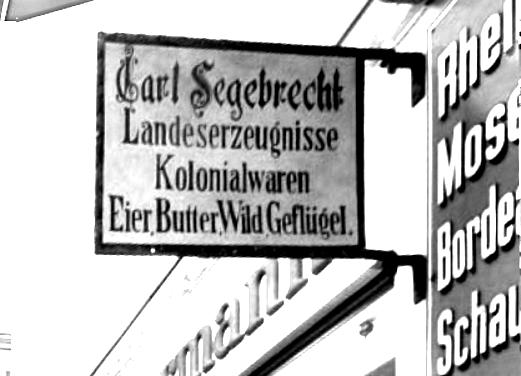
Schriften für Ladenschilder etc. um 1900-1910, was passt?
ich suche passende Schriften für Laden- und Hinweisschilder, ca. von 1900 bis 1910. Nicht unbedingt Frakturschriften. Siehe Schild im Anhang ab Zeile "Landeserzeugnisse". Ich bin Mitglied bei einer Museumseisenbahn und wir möchten den Bahnhof mit entsprechenden Schildern ausstatten. Alle Vorschläge sind willkommen, ich lege mich nicht unbedingt auf das Schriftbild im Anhang fest.
vor 4 Stunden schrieb Ralf Herrmann:
Nicht böse sein, aber das ist falsch gedacht. Die Schilder können durchaus mit bereits etablierten, und damit auch (wesentlich) älteren, Schriften versehen sein. Ich denke da gerade an die Breite Halbfette (Schelter-) Grotesk ... Kurz: Aus dem Jahr 1860, die freie Schrift Works Sans ist da ziemlich ähnlich ...
Hier zwei Postings mit Bezug:
Aber auch andere Schriften kommen da in Frage: Die alten Schriftmuster der Akzidenz Grotesk aus der Zeit von vor 1900.
Und dann sind da noch die Vorläufer der Schriften nach DIN 1451. Da hat Peter einiges im Programm ...
vor 4 Stunden schrieb catfonts:
dann schau mal bei mir, catfonts.de, da ist bestimmt im Stil passendes dabei.
Das waren nun die Serifenlosen. Das von mir geschriebene gilt auch für Antiqua.  Hier was für 1900 ...
Für die Lettern auf dem Schild ist die Vorlage eine der alten, schmal laufenden Schriften aus der Zeit um oder kurz vor 1900 gewesen.  Ich greife mir mal zwei Beispiele raus:
Das nächste Beispiel sind eigentlich drei Schriften mit Namen Theano, alle vom gleichen Designer:
Diese Schriften sind bei mir im E-Katalog auf der Festplatte übrigens in der Unterrubrik Science (Wissenschaft) abgelegt. Diese Schriften kennt man meistens nur noch aus ganz alten Lehrbüchern.
Hier findet man ganz viele thematische Listen: http://www.fontscape.com/
Categories -> Period -> ... Und dann gibt es aus dem passenden Zeitraum einiges:
Ich würde die Rubrik Jugendstil vorschlagen: http://www.fontscape.com/explore?6QH
vor 6 Stunden schrieb Uwe Borchert:
Nicht böse sein, aber das ist falsch gedacht. Die Schilder können durchaus mit bereits etablierten, und damit auch (wesentlich) älteren, Schriften versehen sein. Ich denke da gerade an die Breite Halbfette (Schelter-) Grotesk ... Kurz: Aus dem Jahr 1860, die freie Schrift Works Sans ist da ziemlich ähnlich ...
Also ich hab auf den Satz »Siehe Schild im Anhang ab Zeile Landeserzeugnisse« geantwortet. Das ist eindeutig ein Schildermaler-Werk und kann also nicht mit älteren Schriften gesetzt sein. Und der gesuchte Stil ist eine schmallaufende Antiqua mit typischen Merkmalen genau dieser Zeit (siehe Lucian Bernhard u.a.). Die Liste verweist somit auf passende Schriften. Das ist also mitnichten falsch gedacht.
Da ist er, Dein Denkfehler! ... kann also nicht mit älteren Schriften ... Die Schrift wurde nachgezeichnet und die Vorlage musste nur zu dieser Zeit schon bekannt sein. Wie lange die Schrift schon bekannt war ist erst mal unbekannt. Wichtiger  wäre da: Welche Schriften waren zu dieser Zeit modern? Die Antiqua auf dem Schild entspricht vielen Schriften die gegen Ende des 19ten Jahrhunderts benutzt wurden, also vor 1900. Und natürlich ist da der eine oder andere Nachzügler noch in der Schriftenliste 1900-1909 drinnen. Aber der korrekte Ansatz geht bei der Auswahl schon vor 1900 los und schaut dann was um/nach 1900 modern und beliebt war. Da ist ein halbes Jahrhundert Vorlauf nix ungewöhnliches in typografischen Zeitmaßstäben.
Wem ist es unbekannt? Ich habe bereits darauf geantwortet, dass die Schildermalerarbeit typische Stile eben jener Zeit aufweist. Dieses quirlig expressive »g« findet sich Anfang des 20. Jahrhunderts im deutschsprachigen Raum, jedoch nicht bei den viel biederen Schriften des 19. Jahrhundert. (Daher mein beispielhafter Verweis auf Bernhard.) Lässt sich übrigens mit einem Blick in den Seemann ganz schnell beweisen.
Entsprechend habe ich auf eine passende Liste verwiesen. Ein einzelnen Link ist freilich keine allumfassende Antwort, aber eben auch kein Denkfehler.